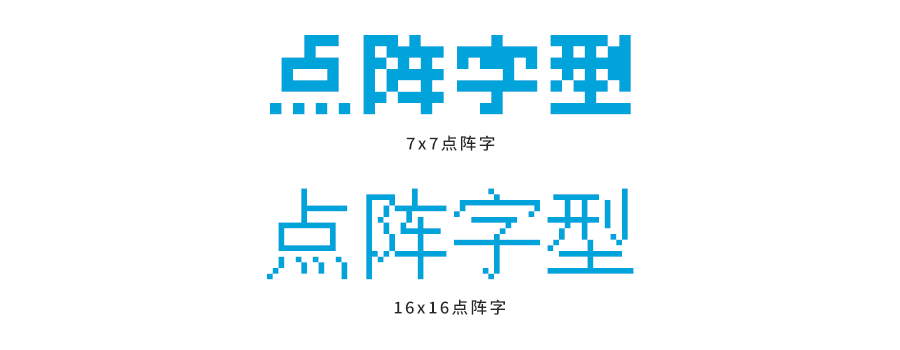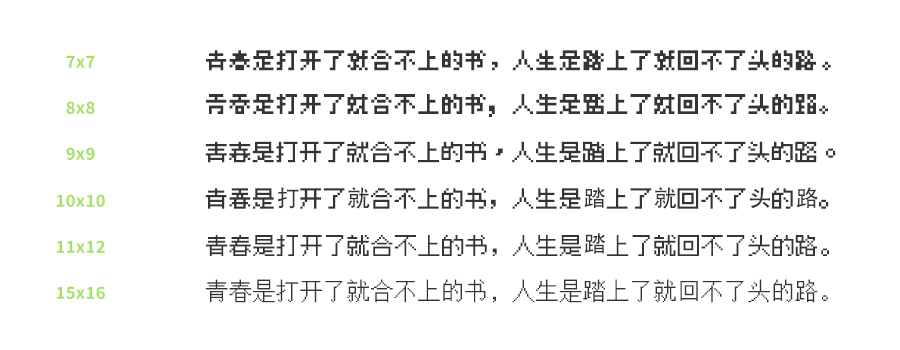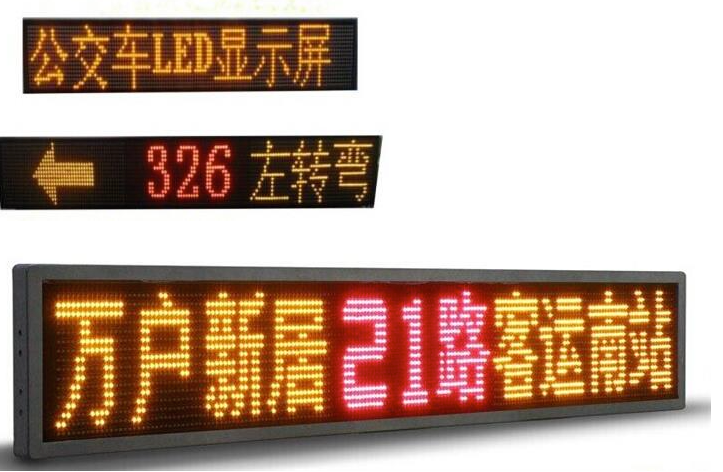
不同大小的点阵字是什么模样呢?以下就是一些例子:
在图例中,我们可以看到,方形空间越大,所能造出的形状就越精细。在较小的空间里,笔画多的字往往需要减省一些笔画以保持清晰。但方形空间增大后,就不需要减省笔画了,还可以将撇、捺等斜笔修饰得更细致,减少放大字型后的锯齿现象。
字型技术后来迈入新时代,可以直接描绘文字的外框,不再需要用点来组成。但点阵字仍有用武之地:公交车的电牌、windows操作系统。到现在的windows操作系统也还预设有点阵字,因为要显示细小的字号时,屏幕像素不高的话就无法显示外框围出来的那种字形。